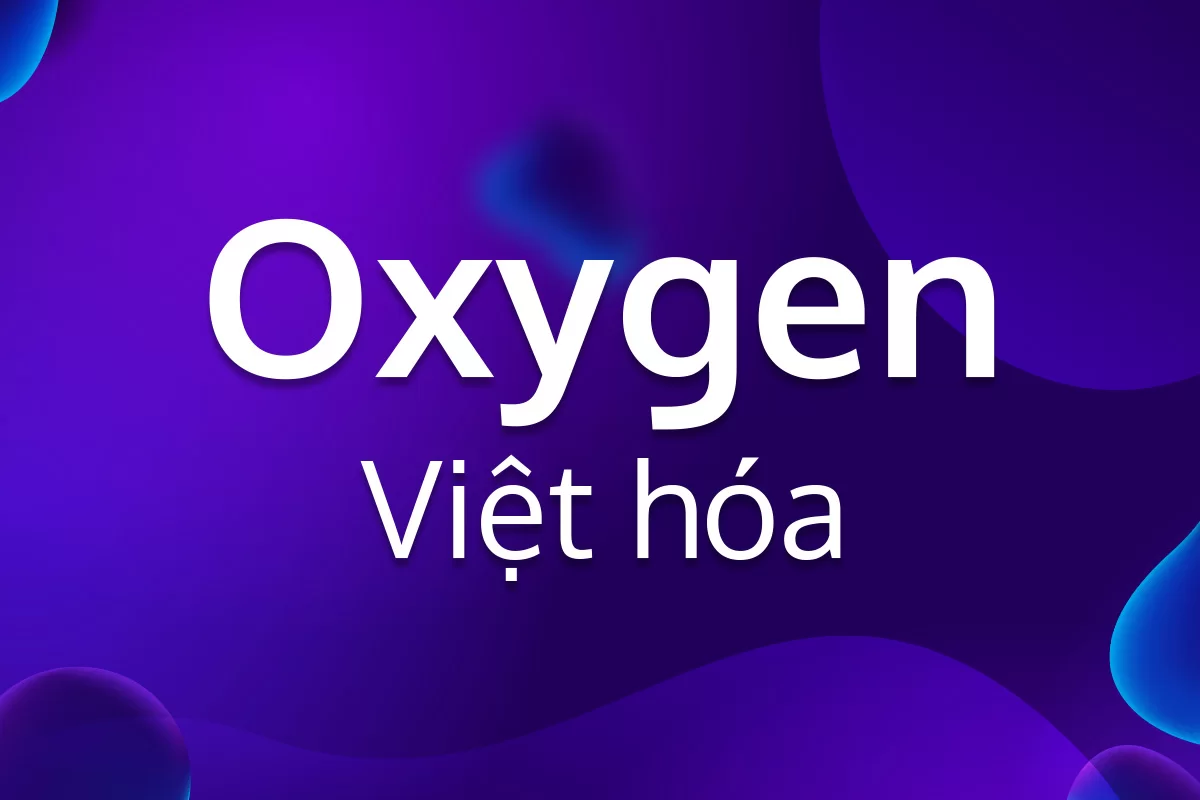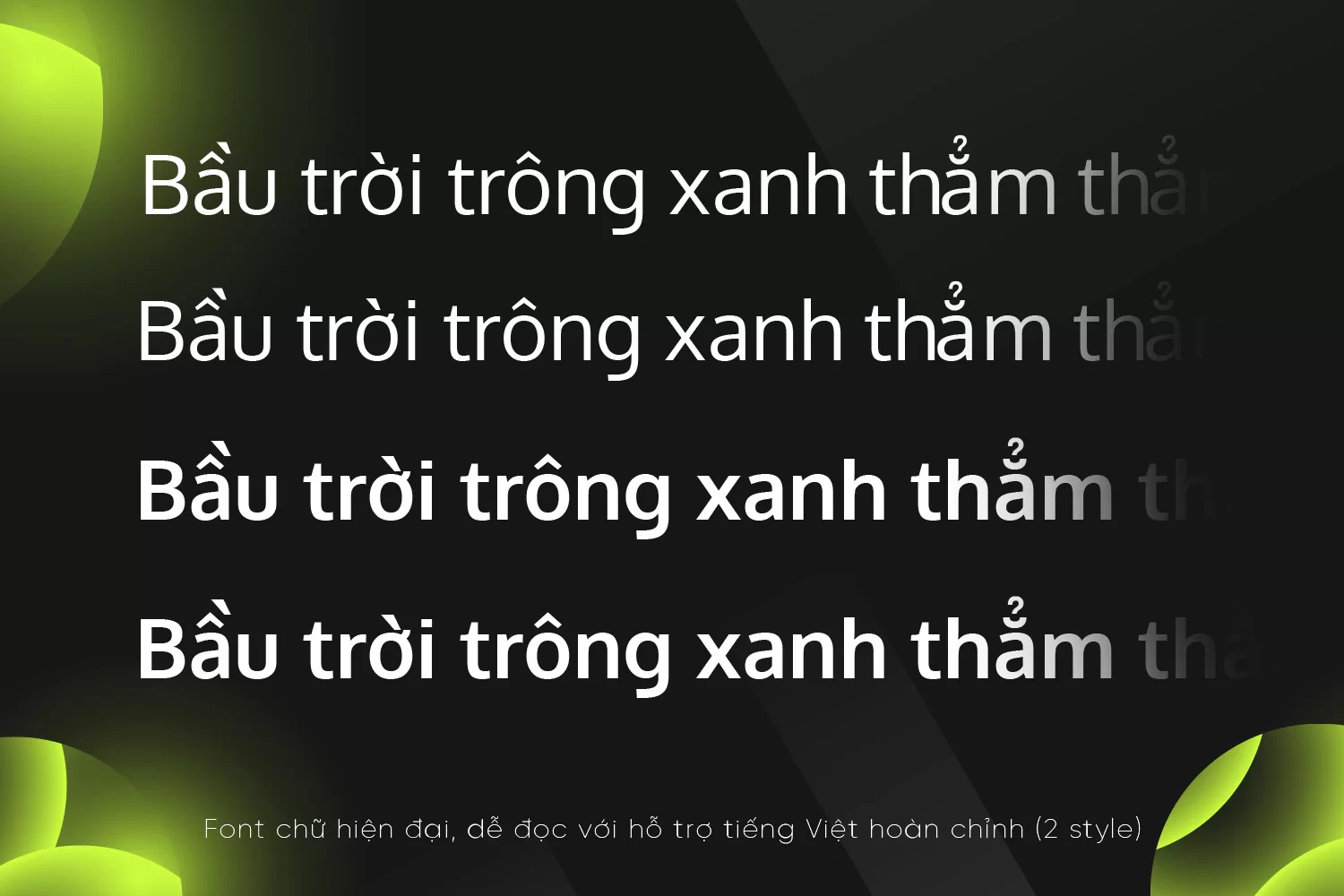
DVN Oxygen là phiên bản Việt hóa của font chữ Oxygen – một typeface hiện đại, sans-serif được thiết kế tối ưu cho giao diện số và trải nghiệm đọc trên màn hình. Với thiết kế rõ ràng, cấu trúc cân đối và khoảng cách chữ thoáng đãng, DVN Oxygen mang lại khả năng hiển thị vượt trội ở mọi kích cỡ. Font thích hợp cho cả giao diện website, ứng dụng di động lẫn thiết kế ấn phẩm in ấn. Bản Việt hóa được tinh chỉnh kỹ lưỡng, giữ nguyên tinh thần nguyên bản trong khi mở rộng đầy đủ bộ ký tự hỗ trợ tiếng Việt, bao gồm dấu và ký tự đặc biệt. DVN Oxygen là lựa chọn lý tưởng cho những ai tìm kiếm một kiểu chữ trung tính, dễ đọc nhưng vẫn mang nét hiện đại và chuyên nghiệp. Phù hợp cho cả nội dung dài lẫn tiêu đề ngắn gọn trong các dự án thiết kế đa dạng.
2 Phiên bản Việt hóa bao gồm: Regular, Bold